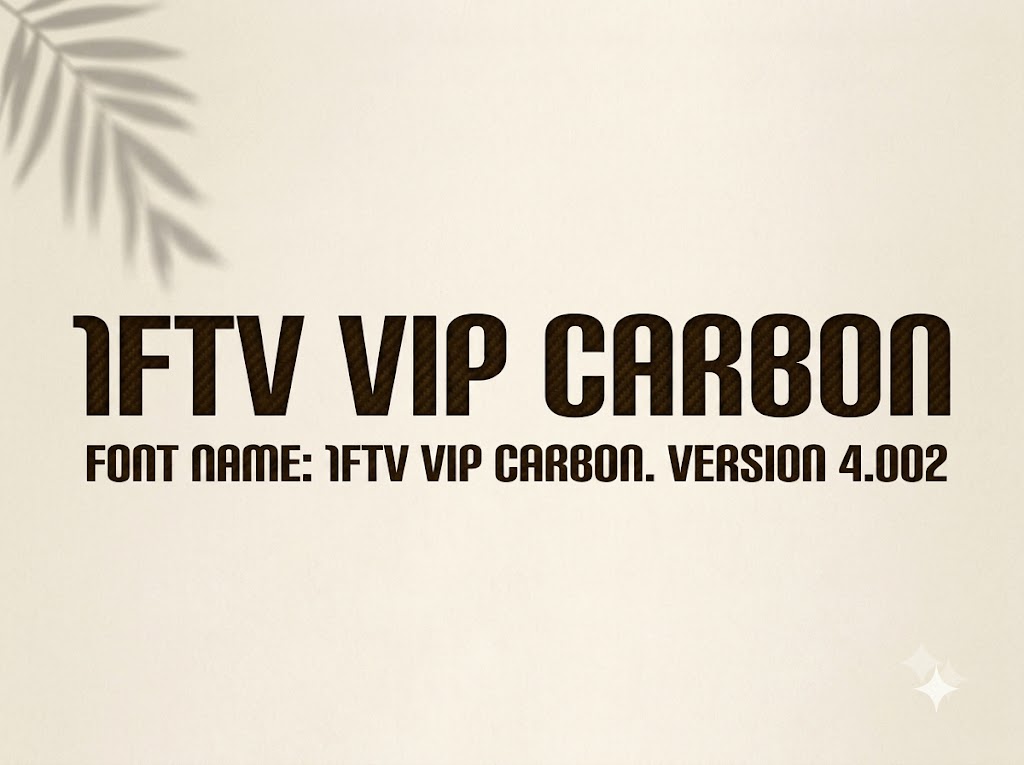
1FTV VIP Carbon
Khi thiết kế các dự án về chủ đề công nghệ, thể thao điện tử (esports) hay cơ khí hiện đại, việc chọn một phông chữ tiêu đề thể hiện được sự vững chãi và bứt phá là bài toán không hề dễ dàng.
Một font chữ quá đại trà hoặc thiếu độ dày cần thiết sẽ khiến ấn phẩm truyền thông của bạn dễ dàng chìm nghỉm giữa hàng ngàn nội dung số khác.
Nếu bạn đang tìm kiếm một làn gió mới đầy góc cạnh, khỏe khoắn để nâng tầm các dòng tiêu đề của mình, font 1FTV VIP Carbon chính là sự lựa chọn không thể bỏ qua.
Giới thiệu về font 1FTV VIP Carbon
Font 1FTV VIP Carbon là một bộ chữ hiển thị (display font) không chân sở hữu phong cách hiện đại, mang hơi hướng công nghệ và cấu trúc hình học tương lai.
Bộ font này đã được cải tiến và tối ưu hóa toàn diện lên phiên bản cao cấp Version 4.002, mang lại sự hoàn thiện vượt trội về mặt đường nét và độ ổn định.
Nhờ các thông số kỹ thuật tối ưu này, phông chữ có khả năng hiển thị vô cùng sắc nét, giúp bạn tự tin ứng dụng trên mọi phần mềm đồ họa chuyên nghiệp mà không lo bị lỗi răng cưa.
Đặc điểm nổi bật của phong cách thiết kế Carbon
Điểm ấn tượng nhất của font 1FTV VIP Carbon nằm ở cấu trúc chữ nén (condensed) với các đường nét dày dặn, mang lại cảm giác vô cùng chắc chắn và uy lực.
Phông chữ được xây dựng theo định dạng All-Caps (viết hoa đồng bộ cho cả hai hệ thống ký tự), giúp các khối chữ khi xếp cạnh nhau luôn đạt được sự cân bằng tuyệt đối về mặt cao độ.
Các góc chữ được bo vát tinh tế, kết hợp khéo léo giữa những nét thẳng dứt khoát và những đường cong khép kín độc đáo ở các ký tự như B, O, R, N, D.
Sự phá cách trong tạo hình này gợi liên tưởng mạnh mẽ đến cấu trúc của sợi carbon bền bỉ, các dòng siêu xe thể thao hay hệ thống vi mạch công nghệ cao.
Để phông chữ vận hành mượt mà trên mọi hệ thống máy tính, phiên bản font 1FTV VIP Carbon đã trải qua quy trình xử lý thông số kỹ thuật vô cùng nghiêm ngặt.
Hệ thống khoảng cách chữ (kerning) và độ giãn dòng đã được căn chỉnh chuẩn xác, giúp văn bản khi đứng cạnh nhau luôn giữ được sự liền mạch và tính thẩm mỹ cao nhất.
Bên cạnh hệ thống chữ cái viết hoa đồng bộ, font còn tích hợp đầy đủ dãy số từ 0-9 cùng hệ thống các ký tự đặc biệt, dấu câu thông dụng (1234567890.:,;'"(!?)+-*/=).
Hình ảnh demo thực tế của font 1FTV VIP Carbon
Để giúp bạn dễ dàng hình dung khả năng co giãn và hiển thị linh hoạt của phông chữ này trên các kích thước khác nhau, hãy cùng xem qua bảng mô phỏng từ file hệ thống image_5f1cc3.png:
Kích thước nhỏ (12pt – 24pt): Nhờ khoảng hở bên trong ký tự (counter) được tính toán khoa học, các khối chữ vẫn giữ được độ sắc nét, dễ đọc và không bị dính nét trên màn hình di động.
Kích thước lớn (36pt – 72pt): Đây là không gian lý tưởng nhất để font chữ phô diễn toàn bộ sự hầm hố, góc cạnh, tạo hiệu ứng thị giác mạnh mẽ nhằm chiếm trọn tâm trí người xem.
Ứng dụng của font Carbon trong thiết kế đồ họa và làm video
Sở hữu nét cá tính mạnh mẽ và cấu trúc hình khối hầm hố, font 1FTV VIP Carbon mở ra không gian ứng dụng rộng lớn cho các dự án truyền thông:
Thiết kế Poster, Banner Gaming và Esports: Hoàn hảo cho các giải đấu thể thao điện tử, ảnh bìa livestream, hoặc poster giới thiệu các tựa game hành động, giả tưởng.
Làm tiêu đề video ngắn (TikTok, Reels, Shorts): Giúp các từ khóa chính (keywords) nổi bật ngay từ cái nhìn đầu tiên, kích thích thị giác và giữ chân người xem lướt chậm lại.
Ảnh thu nhỏ YouTube (Thumbnail): Đặc biệt hiệu quả với các kênh thuộc chủ đề công nghệ, review xe, khoa học viễn tưởng hoặc các nội dung thể thao vận động mạnh.
Nhận diện thương hiệu công nghiệp: Phù hợp làm logo dạng chữ khối, bao bì sản phẩm hoặc ấn phẩm truyền thông cho các nhãn hàng thời trang streetwear, phụ tùng cơ khí, đồ điện tử.